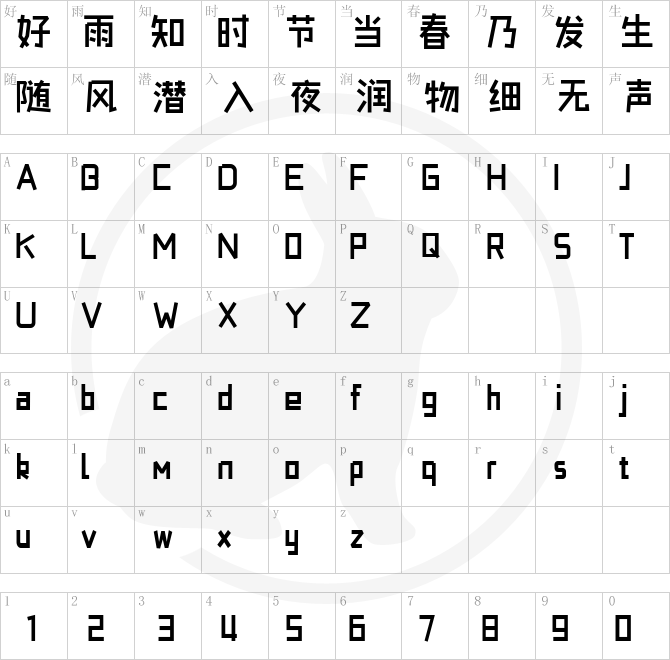
YEFONTDaiBanHei
YEFONTDaiBanHei,这款字体结构工整、笔画清晰,兼顾美观与易读性,适用于标题、正文、海报、包装、LOGO 等多种场景。字形优雅稳定,风格百搭耐看,适配日常排版与创意设计,让文字呈现更舒适、更具质感。YEFONTDaiBanHei一笔一画,皆是细节,以均衡的比例、流畅的线条打造舒适视觉体验,字形端正大气,风格简约现代。无论是商业设计、品牌宣传还是日常排版,都能轻松驾驭,让文字更有格调与力量。YEFONTDaiBanHei字体下载。